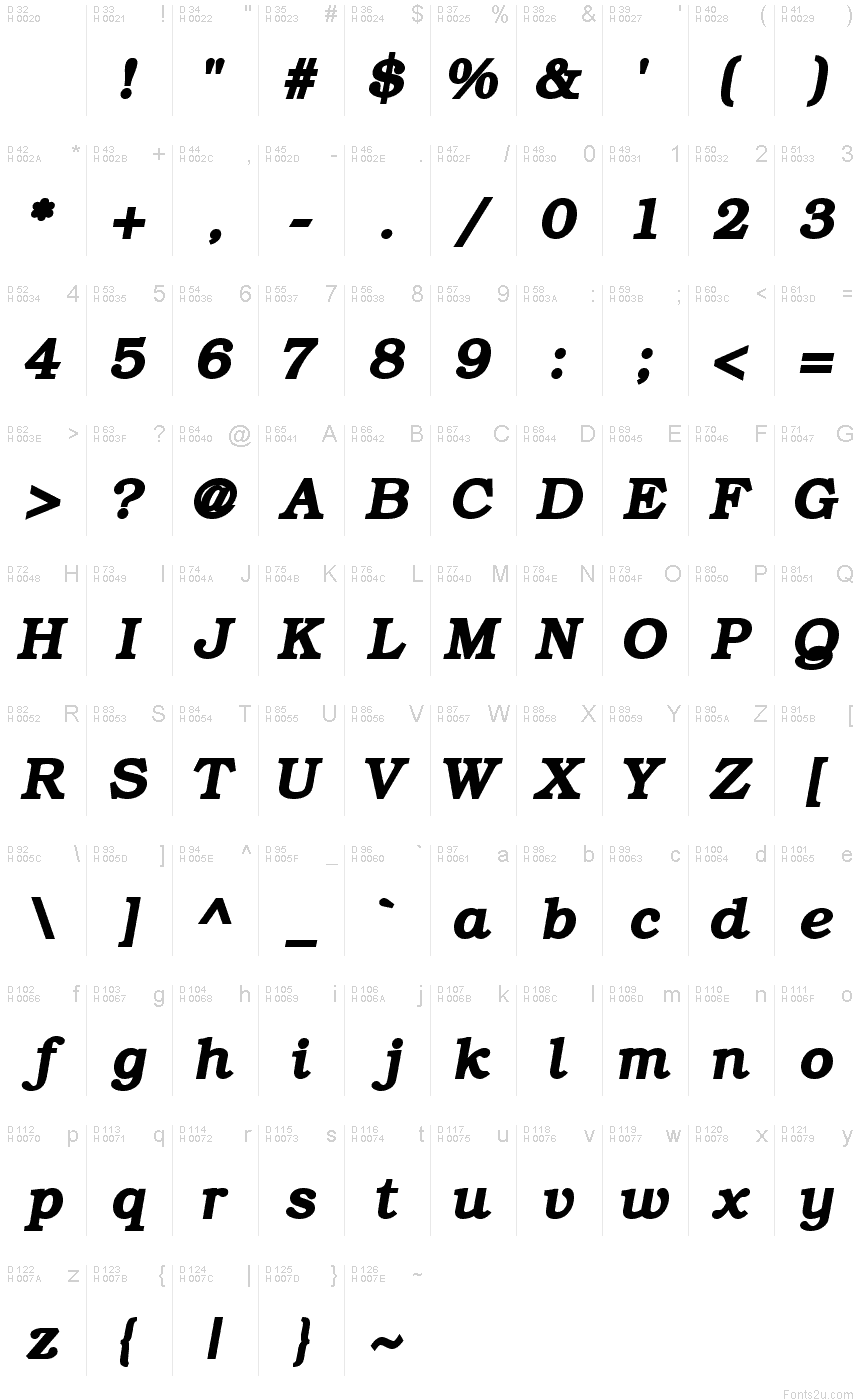
ER Bukinist 866 Bold Italic
ER Bukinist 866 Bold Italic autorstwa Gavina Helfa to bezpłatny, książkowy krój szeryfowy. Jest solidny, a jego atramentowe, pochylone kreski przywodzą na myśl klasyczną, zaczytaną twardą oprawę. W ramach rodziny ER Bukinist 866 ta odmiana kursywy dodaje głębokiego, płynnego rytmu – litery pewnie pochylają się do przodu, zachowując przy tym gęstość i czytelność nawet w mniejszych nagłówkach.
Dzięki ER Bukinist 866 Bold Italic nadasz wagę i dynamikę okładkom książek, tytułom rozdziałów, literackim plakatom, nagłówkom magazynów, opakowaniom butikowym, menu kawiarni czy logotypom autorów. Kompaktowe światło sprawia, że długie tytuły pozostają zwarte i wyraziste, więc nie tracisz miejsca na podkreślanie. Połącz ten darmowy font z czystym, groteskowym krojem bezszeryfowym w tekście głównym, aby jego bogate, pochylone formy nadały charakteru Twojemu projektowi.